我们都知道,在人类还没有出现明确文字使用的时候,智慧的古代人是用甲骨文来记东西和交流的,甲骨文就是属于一种符号字体吧,只不过这种符号字体比其他所有字体都要出现得早,而且文化价值也比较高。遇到不认识的符号字体怎么办呢,我们可以通过搜字体网的字体识别功能来查找对应的字体。
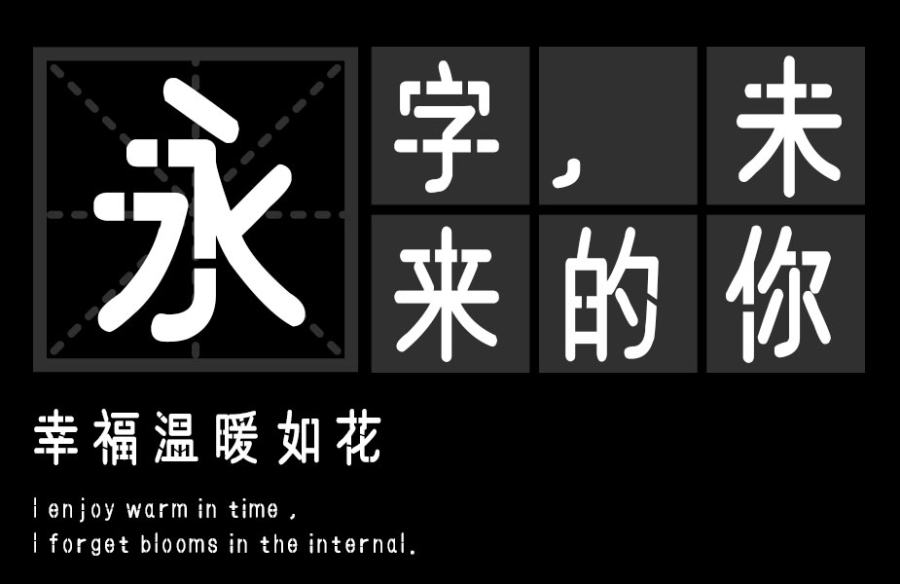
使用符号字体让文字看起来更加具有文字的趣味性和灵活性,丰富了文字的形式和人们表达思想的方式。当看到一些不认识的符号时我们也可以通过寻找图片上的字体来搜索想要的字体。
符号代表一些东西,具有很多种不同的意义。比如象征着我们生活中的某一件事情又或者代表着我们日常生活中要用到的某件用品,又或者代表着一种语言文字...... 实在是太多意义了,没有进行深入的研究,我们根本无法总结归纳出符号字体的所有意义。